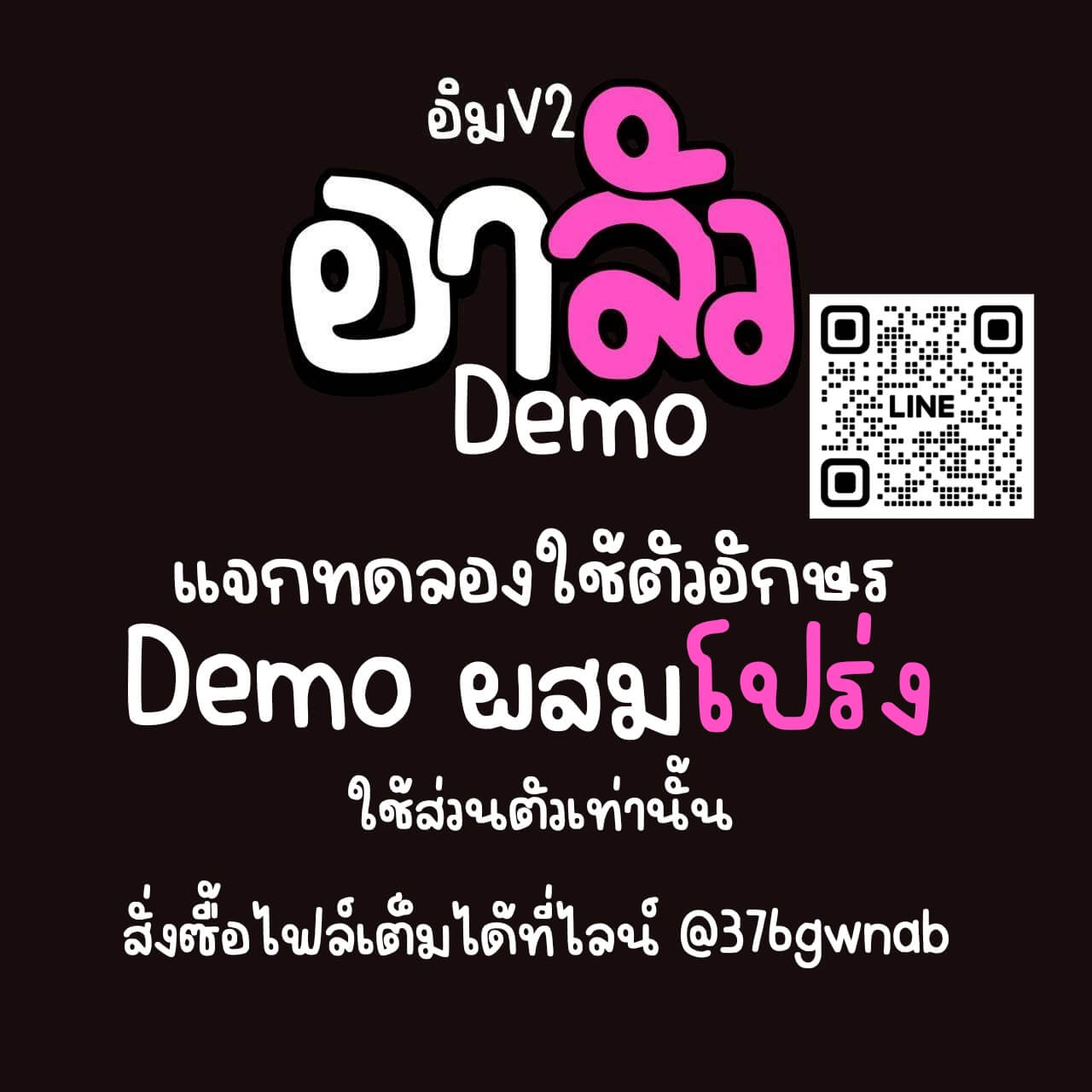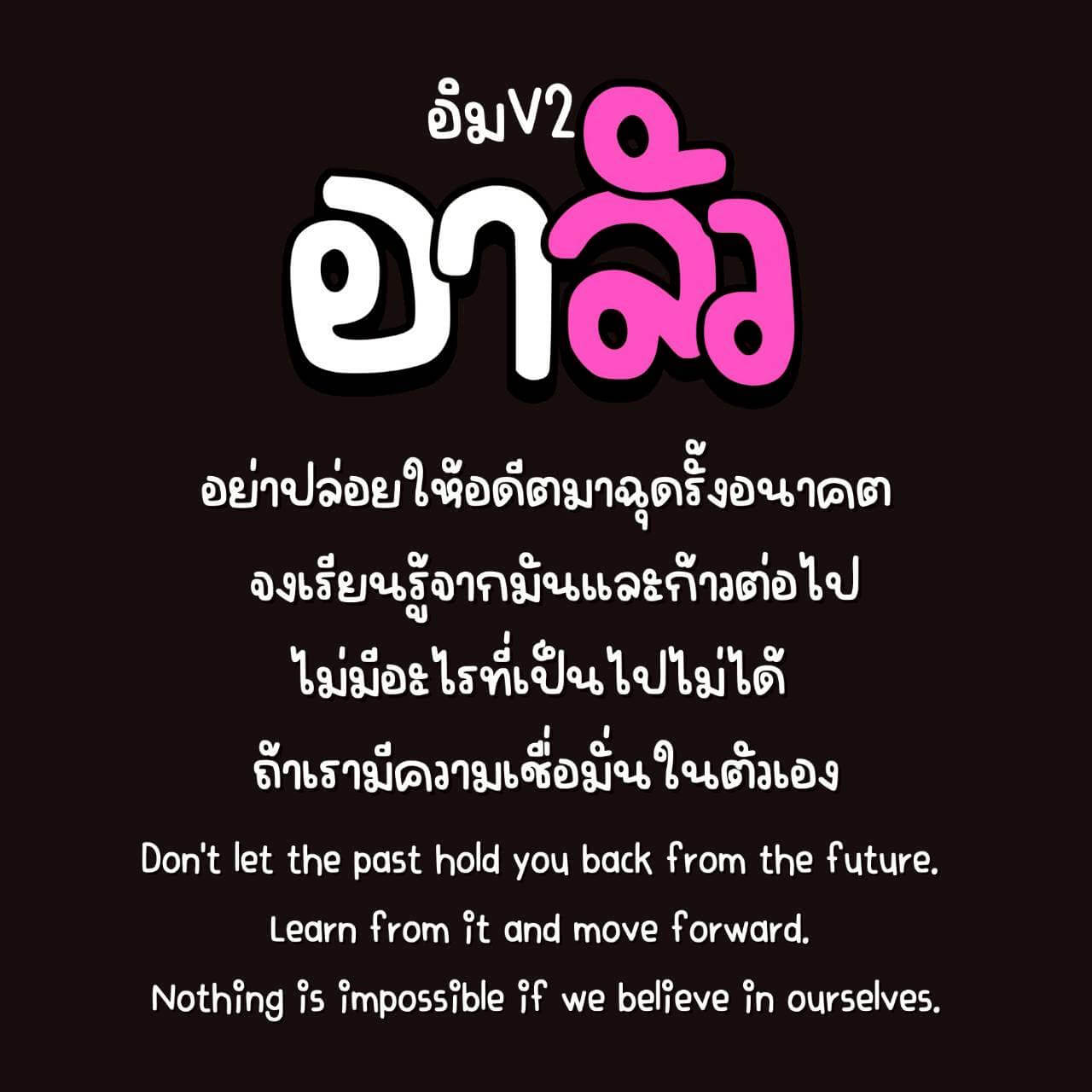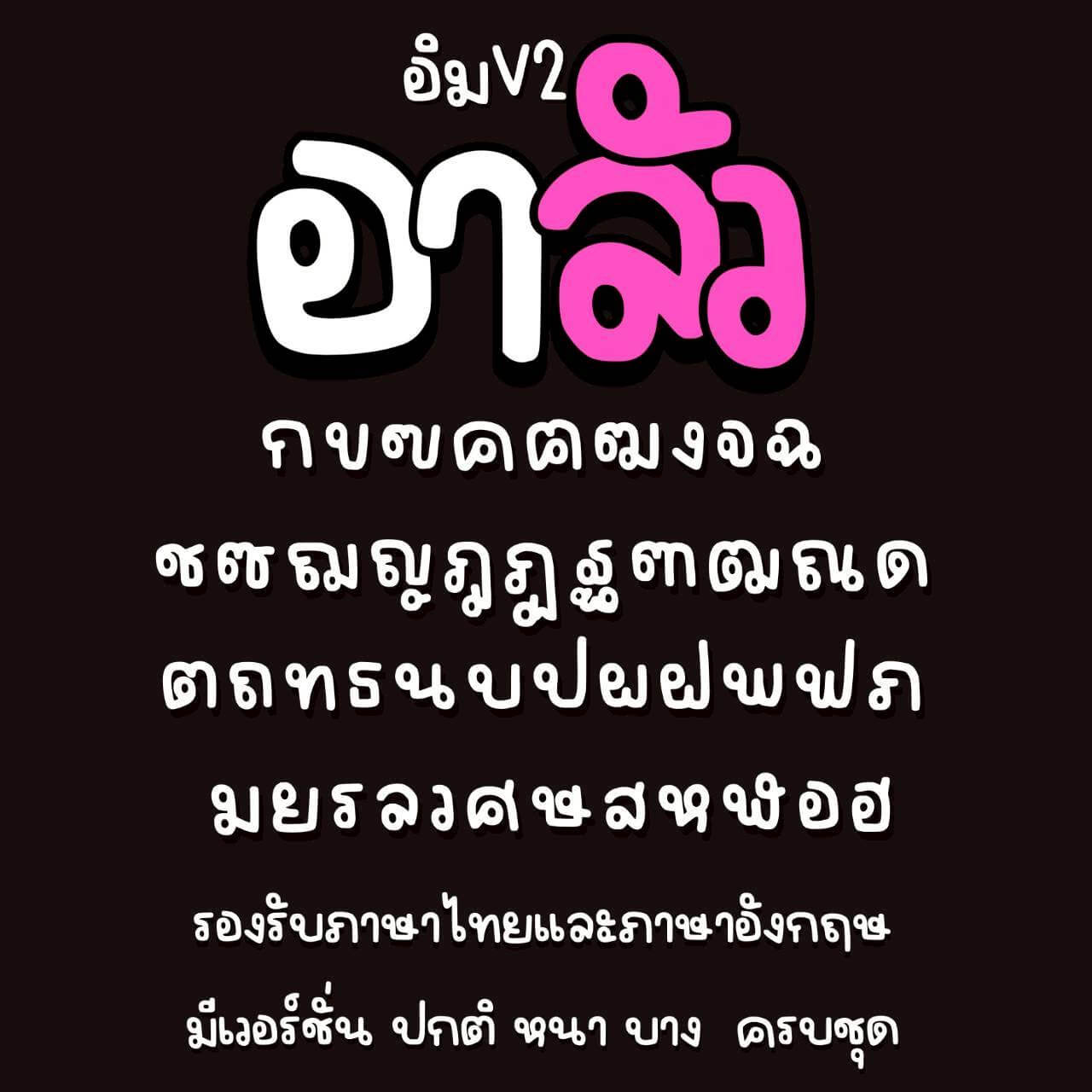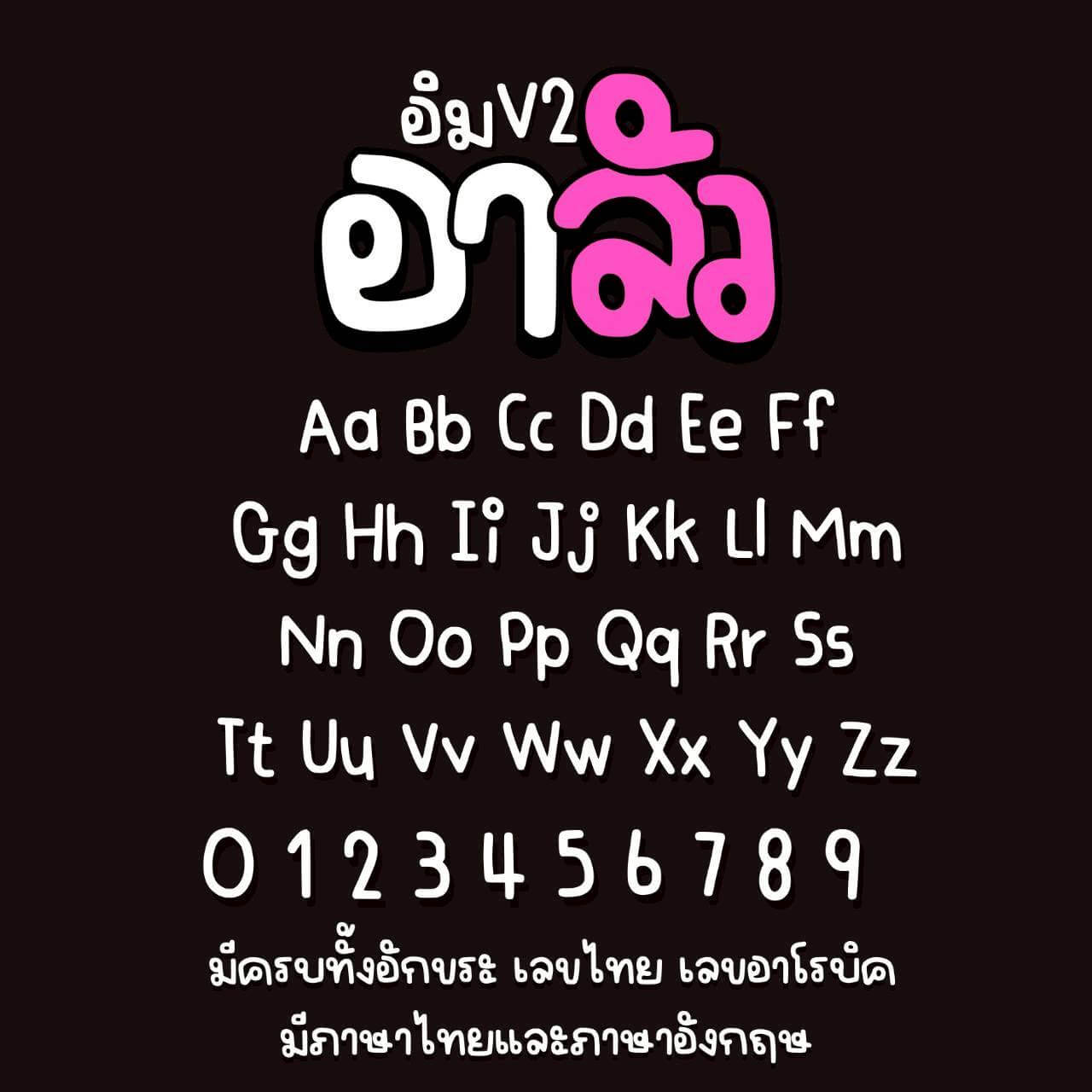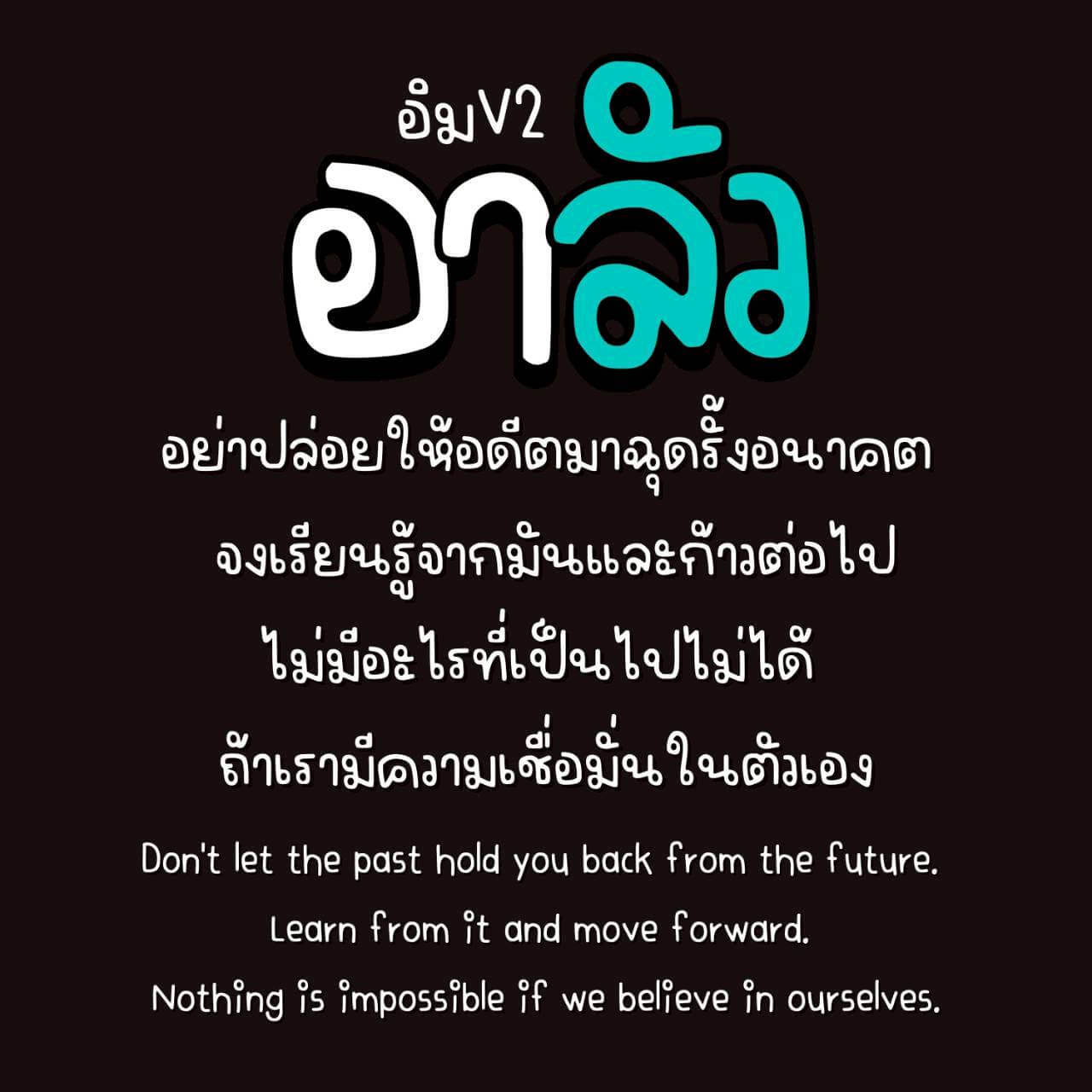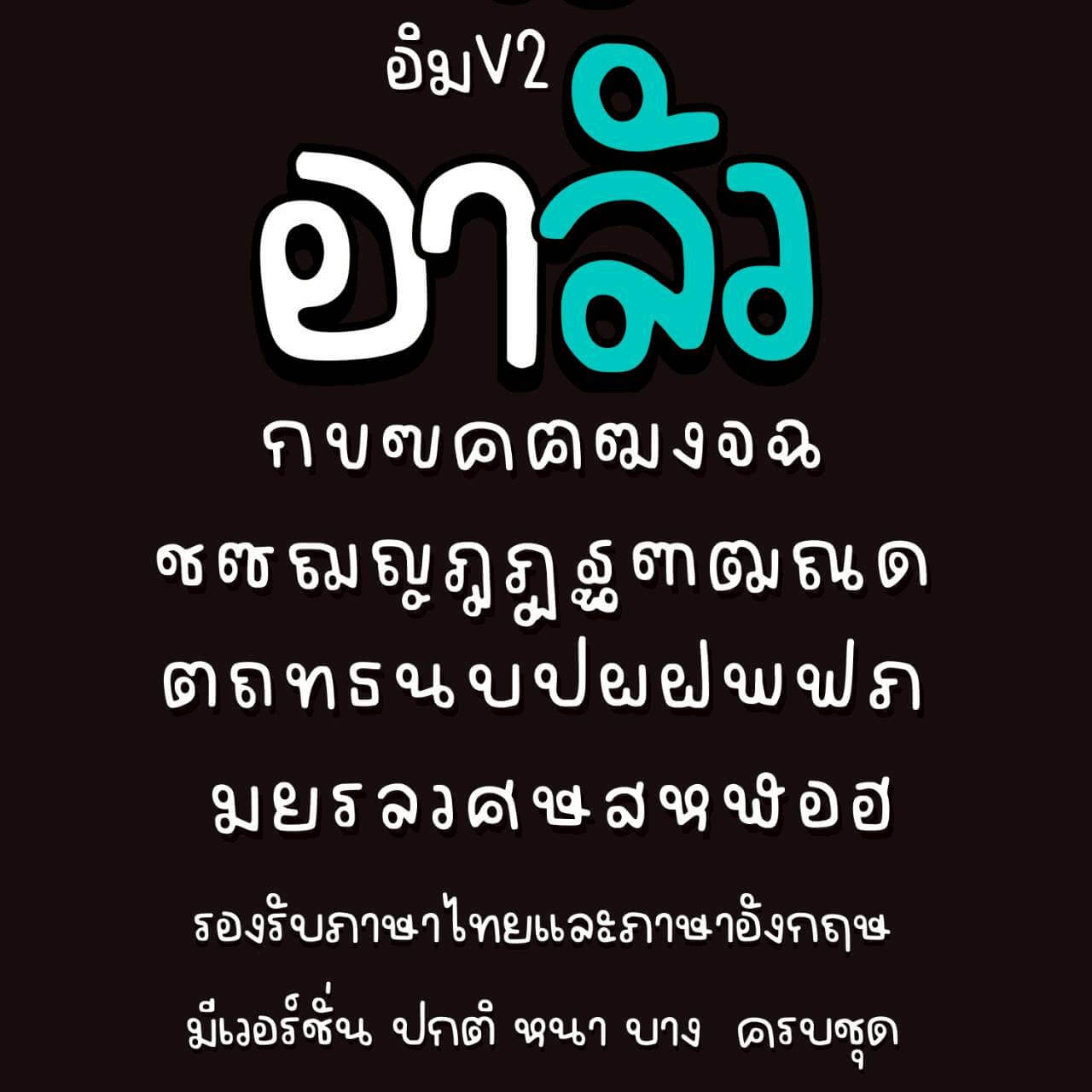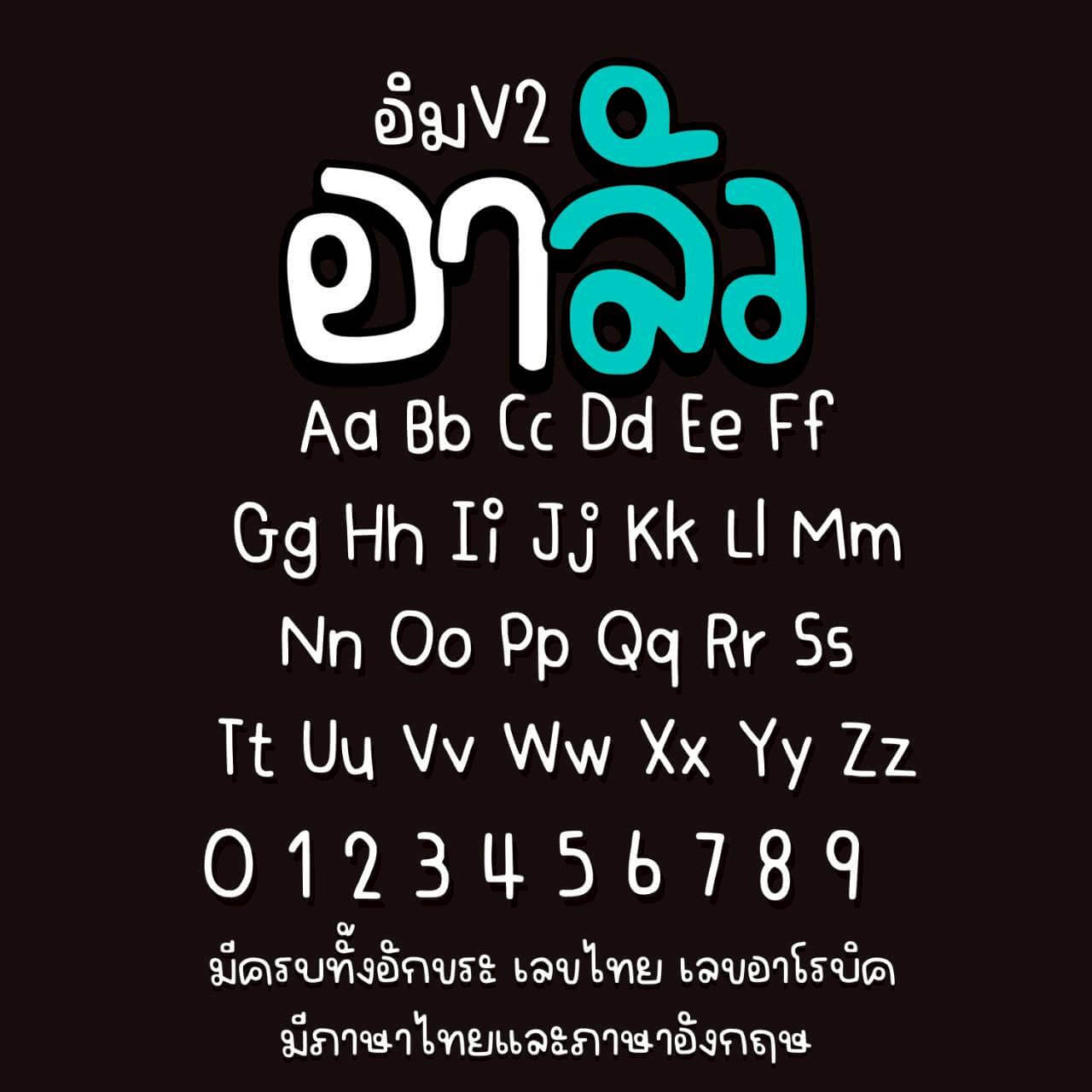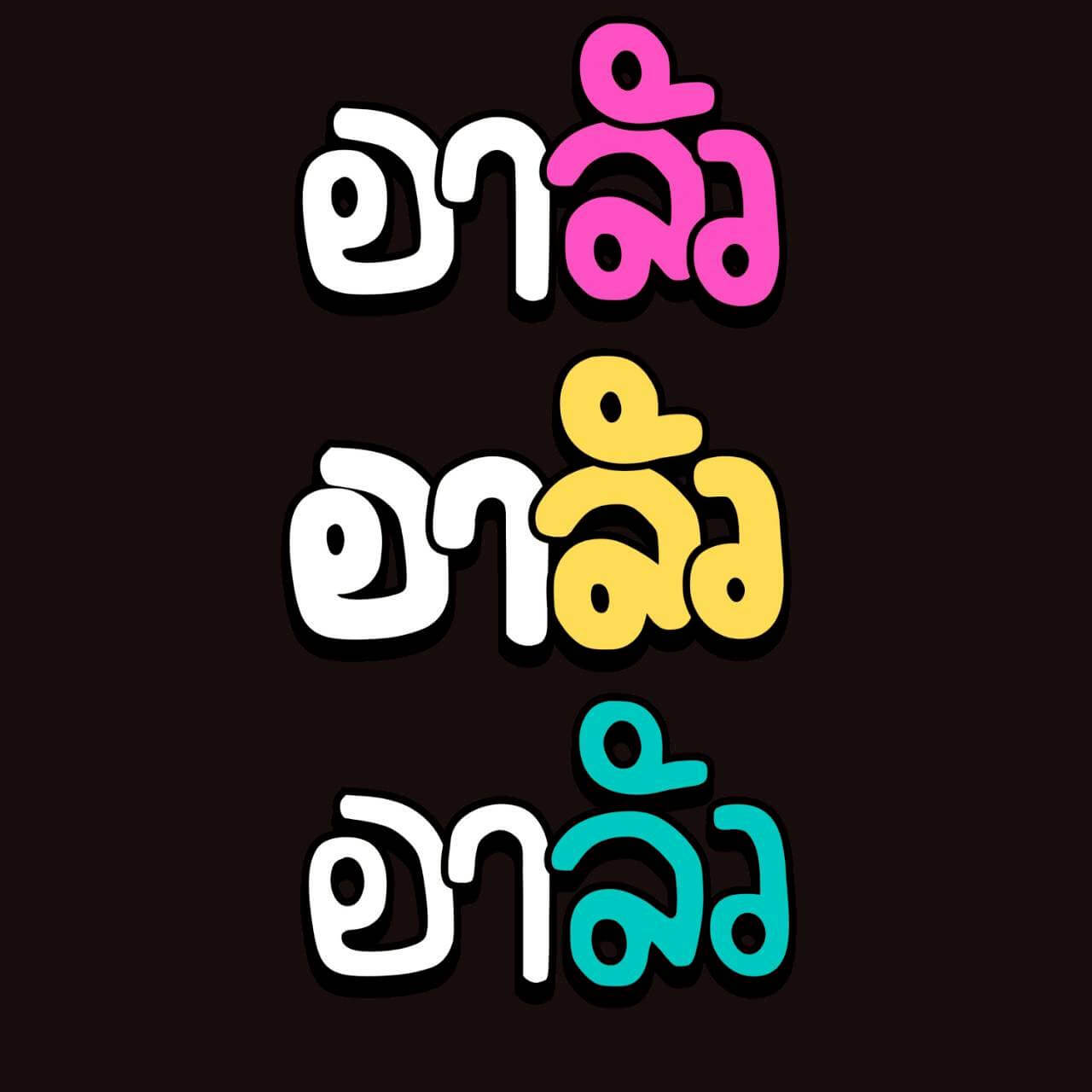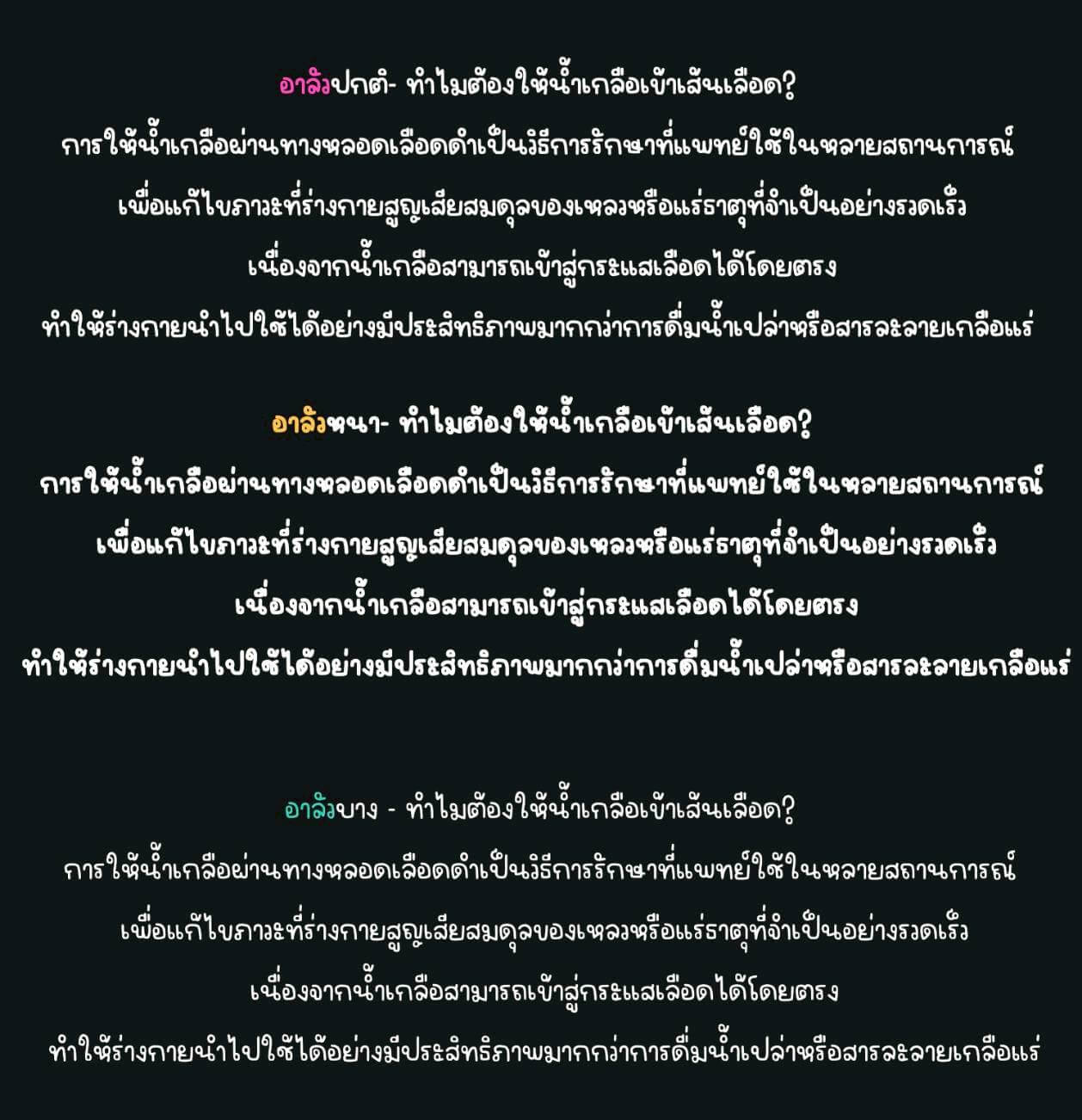
IMTYC อิมอาลัว ฟอนต์ – ปรับสระเรียบร้อย รองรับการใช้งานบนทุกโปรแกรมนะคะ
เหมาะกับทุกสายครีเอเตอร์ ไม่ว่าจะใช้ทำป้าย ข้อความ โพสต์ หรือคอนเทนต์น่ารักๆ
จะได้รับทั้งชุด 3 น้ำหนัก (ปกติ หนา บาง)
อาลัว (IMTYC A-lua)